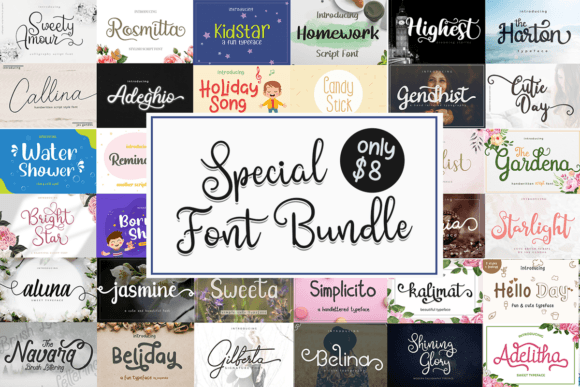
Special Font Bundle
適切なデザイン要素を見つけるのは難しい場合がありますが、Special Font Bundleは作品を即座に引き立てる優れたコレクションを提供します。
POD(オンデマンド印刷)製品、結婚式の招待状、またはソーシャルメディアのグラフィックを作成している場合でも、Special Font Bundleは理想的です。